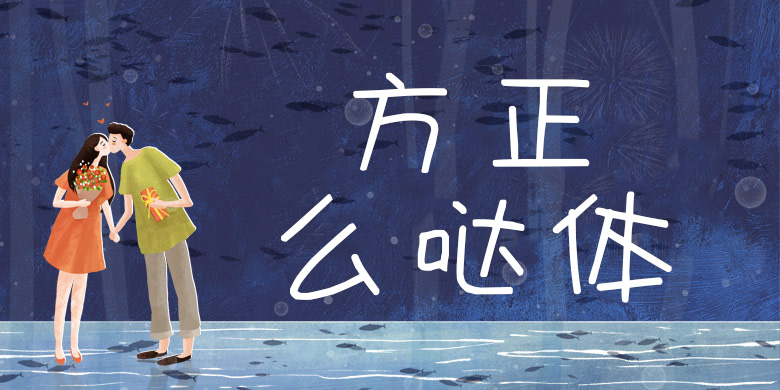
方正手迹-么哒体
方正手迹-么哒体,这款字体结构工整、笔画清晰,兼顾美观与易读性,适用于标题、正文、海报、包装、LOGO 等多种场景。字形优雅稳定,风格百搭耐看,适配日常排版与创意设计,让文字呈现更舒适、更具质感。方正手迹-么哒体一笔一画,皆是细节,以均衡的比例、流畅的线条打造舒适视觉体验,字形端正大气,风格简约现代。无论是商业设计、品牌宣传还是日常排版,都能轻松驾驭,让文字更有格调与力量。方正手迹-么哒体字体下载。
一款卡通风格的POP创意字体,部件线条简单,重心偏中,字面较大,有良好的辨识度。适用于现代诗歌、短文的排版,以及屏显、影视综艺,及文化、商业类品牌的广告语设计。